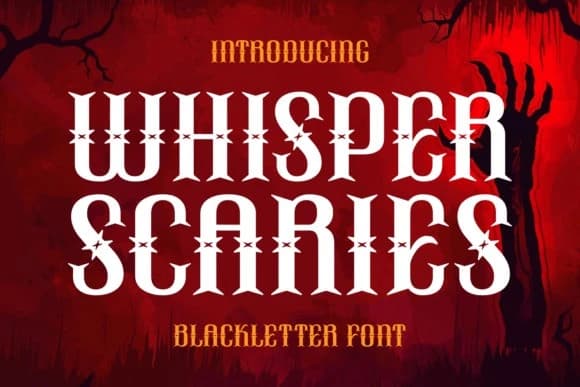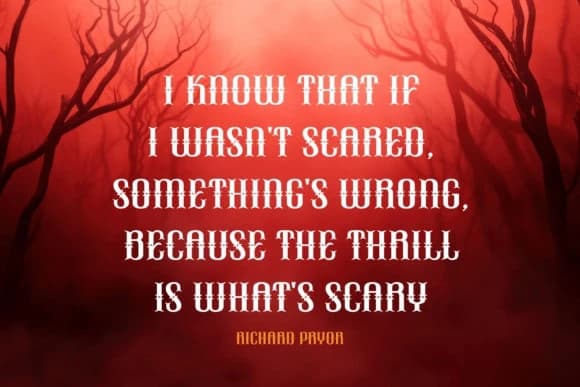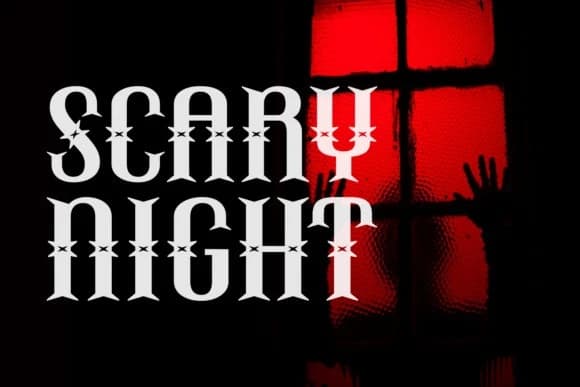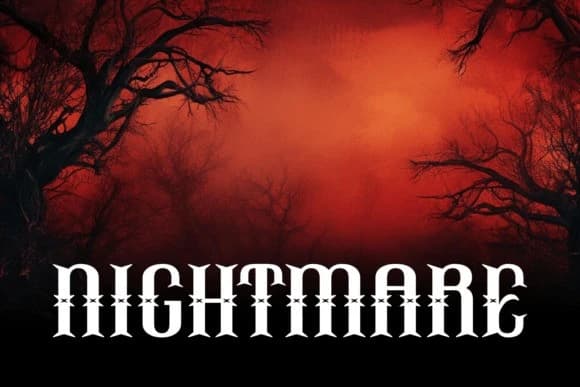
Whisper Scaries Font
Whisper Scaries Font, blackletter ve vintage stilinin benzersiz bir birleşimidir; bu birleşim, uğursuz karanlık ile zamansız çekiciliğin hayranlık uyandıran bir karışımını yaratır. Temiz ve özenle tasarlanmış bir font olarak pek çok farklı kullanım alanına rahatlıkla uyum sağlar.